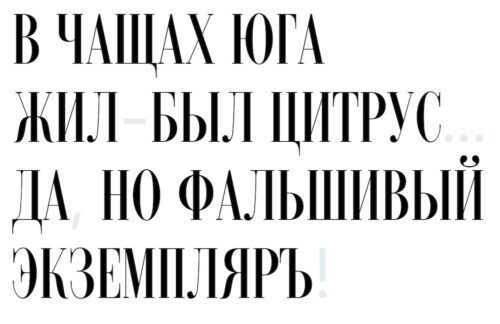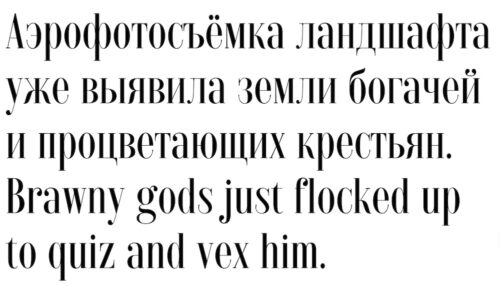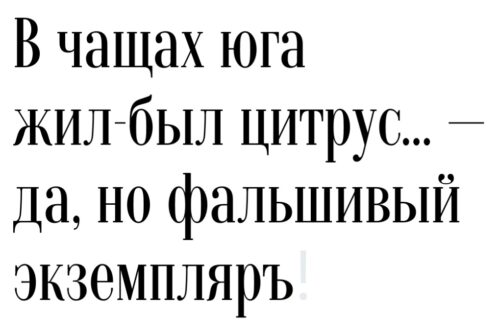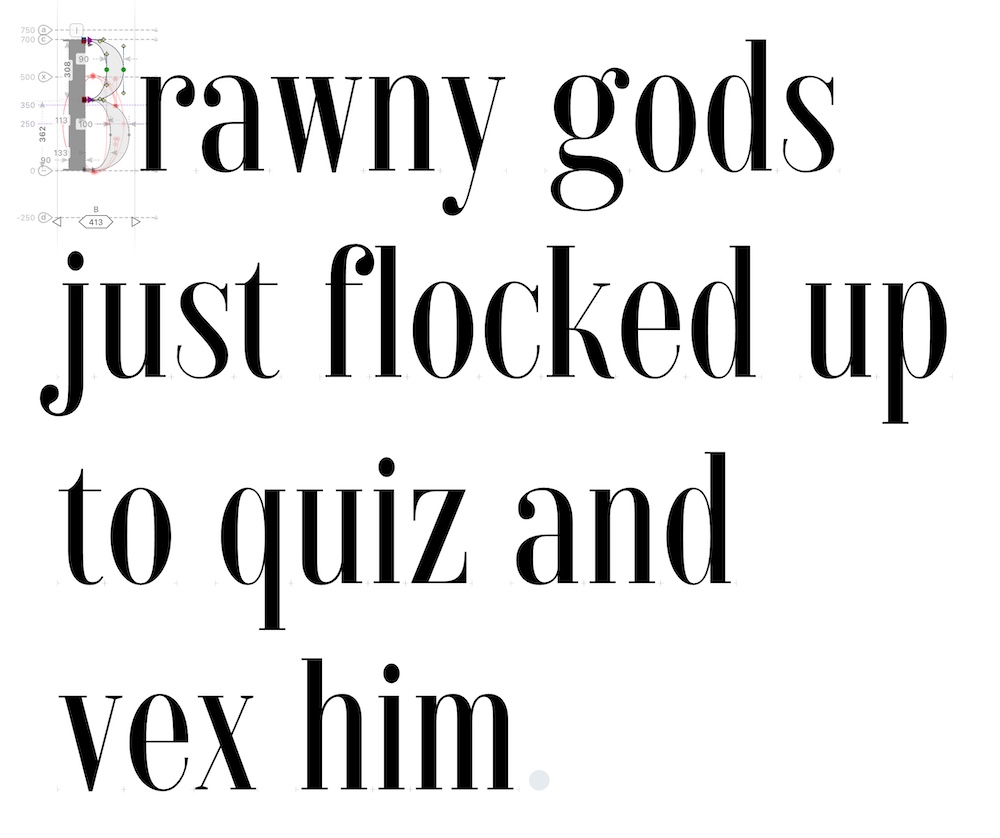
2026-08-09 – Начал делать контрастную антикву.
2026-08-10 – Основную кассу сделал (цифр пока нет), уже кажется, что контраст слишком сильный, тонкие штрихи надо бы сделать толще.
2026-08-18 – Сделал чуть менее контрастную версию шрифта и тут же использовал ее в работе – обложке красивой книги. Для этого добавил пару альтернативных букв с росчерками.